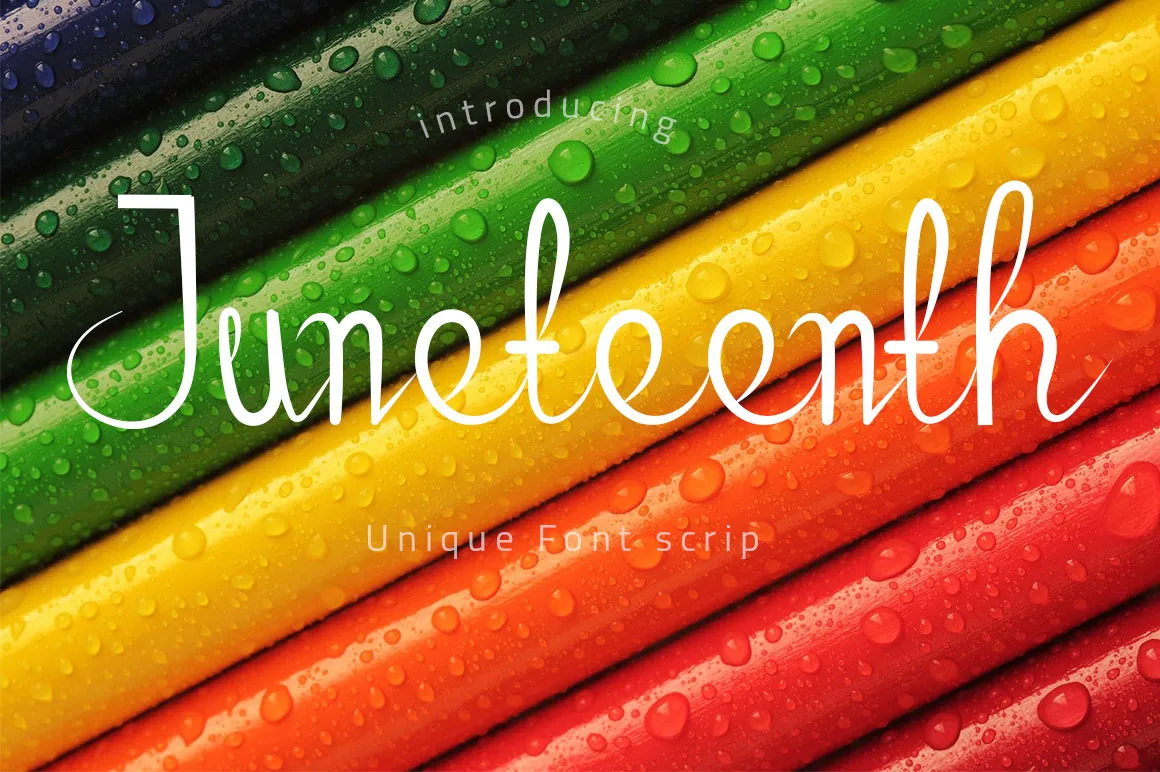
Aqui está uma versão do texto solicitado: Esta fonte é perfeita para quem busca uma combinação única de simplicidade e personalidade no seu design. Criada pelo designer Muhamma Zamroni, a ‘Juneteenth Font’ tem uma graça especial que faz dela um ótimo candidato para criar logos memoráveis, estilos de marca distintos ou citações impactantes. Cada letra é única e envolvente, trazendo vida aos seus projetos gráficos. Com seu toque quase mágico na escrita manuscrita, a ‘Juneteenth Font’ se torna o ideal para qualquer designer que deseja explorar a beleza da tipografia em uma linguagem familiar e acessível. Esta fonte é como um amigo fiel que acompanha você pelos mais diversos projetos gráficos, oferecendo um toque único sempre que for necessário. Para quem busca personalidade e originalidade na sua arte digital, a Juneteenth Font é uma excelente escolha para aqueles que buscam fazer suas ideias realmente brilhar. Suave mas poderosa, essa fonte atua como um catalisador de criatividade, elevando seus projetos à próxima dimensão.